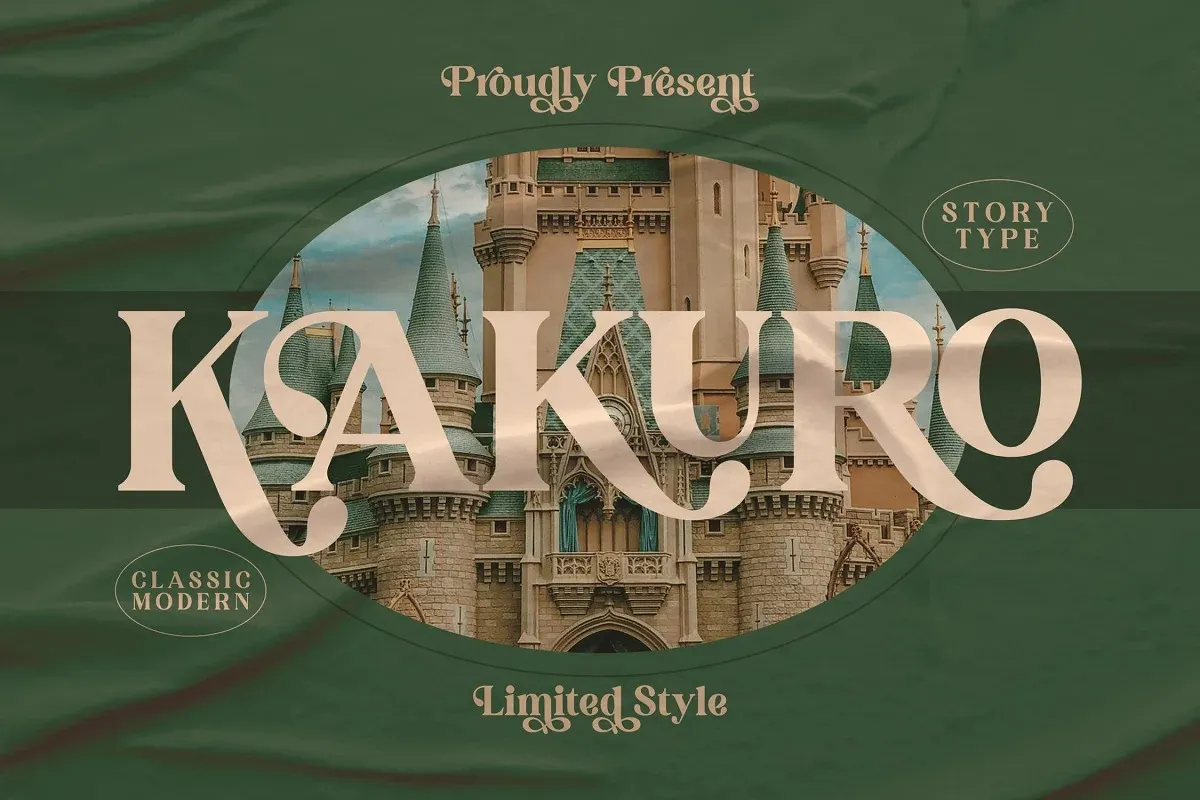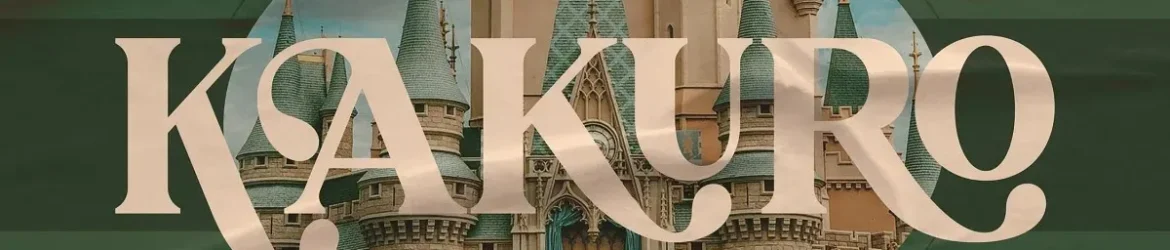
A Kakuro Font é uma elegante fonte serif com alta contração, meticulosamente criada para garantir sua qualidade premium e seu aspecto luxuoso. Esta tipografia perfeito para logotipos de luxo, títulos de livros ou filmes, marcas de moda, revistas, calças, escrita em letras grandes, citações e muito mais. Kakuro oferece uma aparência sofisticada que será o complemento ideal para qualquer projeto de design que busque um toque de elegância e luxo, seja ele impresso ou digital. Opte por Kakuro quando precisar de uma fonte serif de alta qualidade que não apenas se destaca em sua página, mas também reflete a natureza sofisticada de seu trabalho.